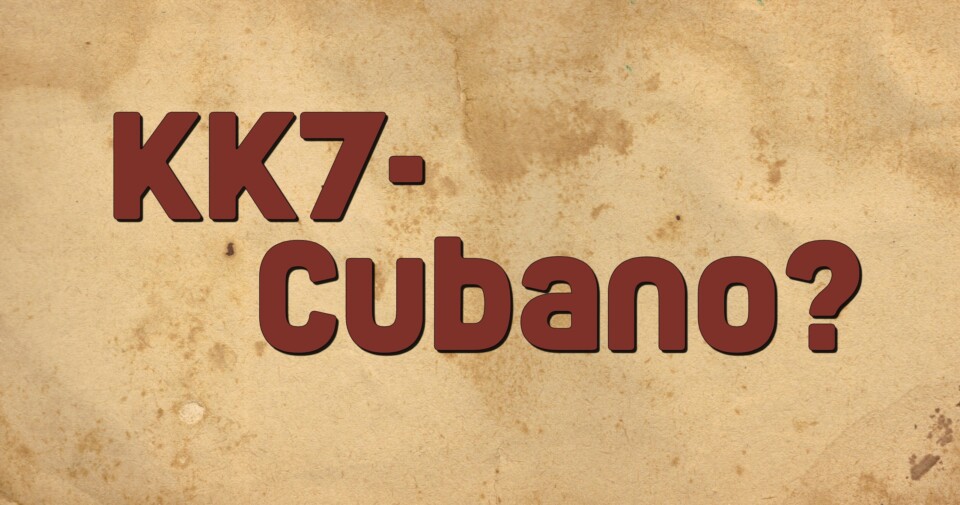
Giới thiệu về bộ Font Việt Hóa KK7-Cubano?
Trong thế giới đồ họa hiện đại, việc tìm kiếm một bộ Font Chữ vừa mang nét cổ điển vừa hiện đại là điều không hề dễ dàng. Bộ Font Việt Hóa KK7-Cubano? chính là giải pháp hoàn hảo cho các bạn học sinh và giáo viên trong việc thiết kế slide bài giảng hoặc báo tường. Với các đường nét bo tròn dày dặn, font chữ này tạo nên cảm giác thân thiện nhưng vẫn giữ được sự chắc chắn cần thiết cho các tiêu đề lớn.
Đặc điểm nổi bật của Font Việt Hóa KK7-Cubano?
Thiết kế ấn tượng và dễ đọc
Đặc trưng lớn nhất của Font Việt Hóa KK7-Cubano? nằm ở cấu trúc không chân (sans-serif) với các góc được làm mềm mại. Điều này giúp nội dung trở nên nổi bật trên các phông nền phức tạp. Trong môi trường học đường, kiểu chữ này giúp học sinh dễ dàng theo dõi bài học từ xa, giảm mỏi mắt nhờ khoảng cách các ký tự được tối ưu hóa cực kỳ chuyên nghiệp.
Khả năng tương thích và ứng dụng đa dạng
Bộ font này đã được việt hóa đầy đủ các dấu câu, đảm bảo không bị lỗi font khi gõ tiếng Việt. Bạn có thể sử dụng nó trong các phần mềm phổ biến như PowerPoint, Photoshop hay Canva. Ngoài việc làm tiêu đề, nó còn rất phù hợp để in ấn áo đồng phục lớp hoặc làm banner sự kiện nhà trường nhờ vẻ ngoài năng động và tràn đầy năng lượng sáng tạo.